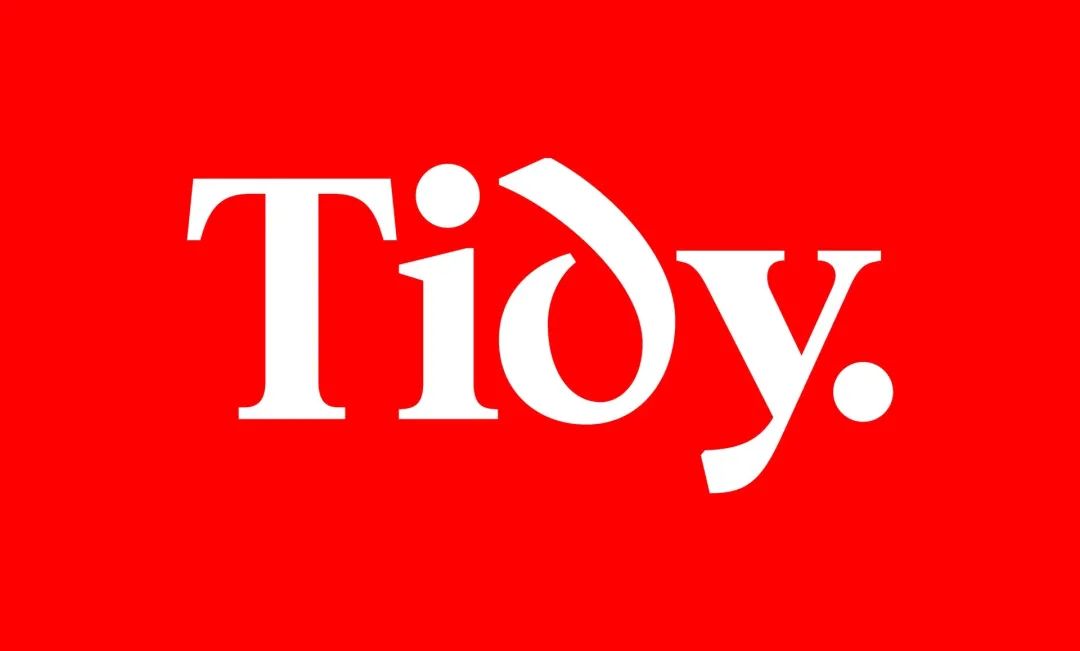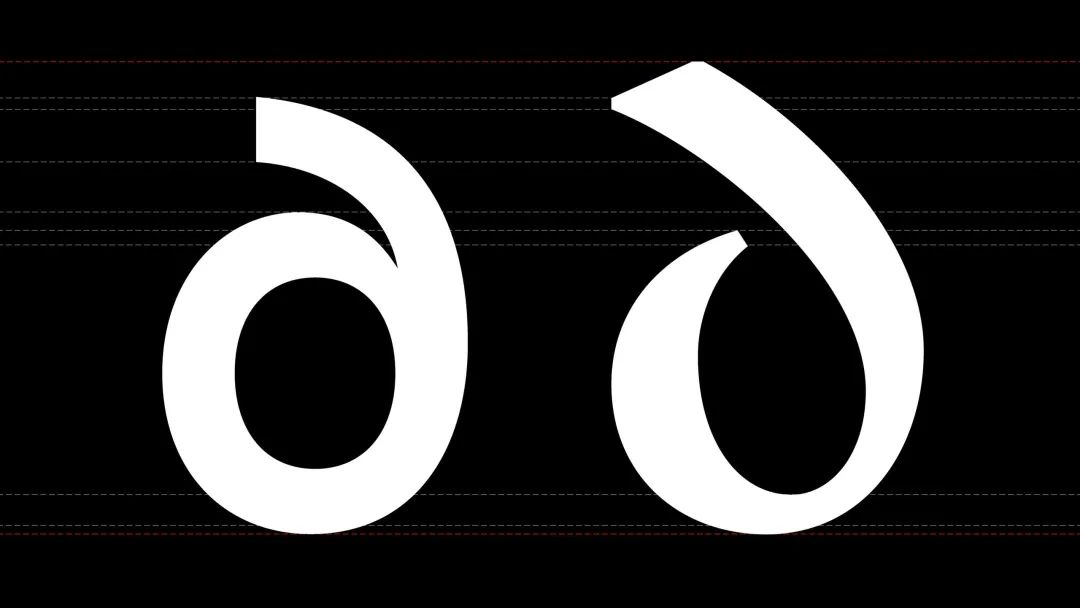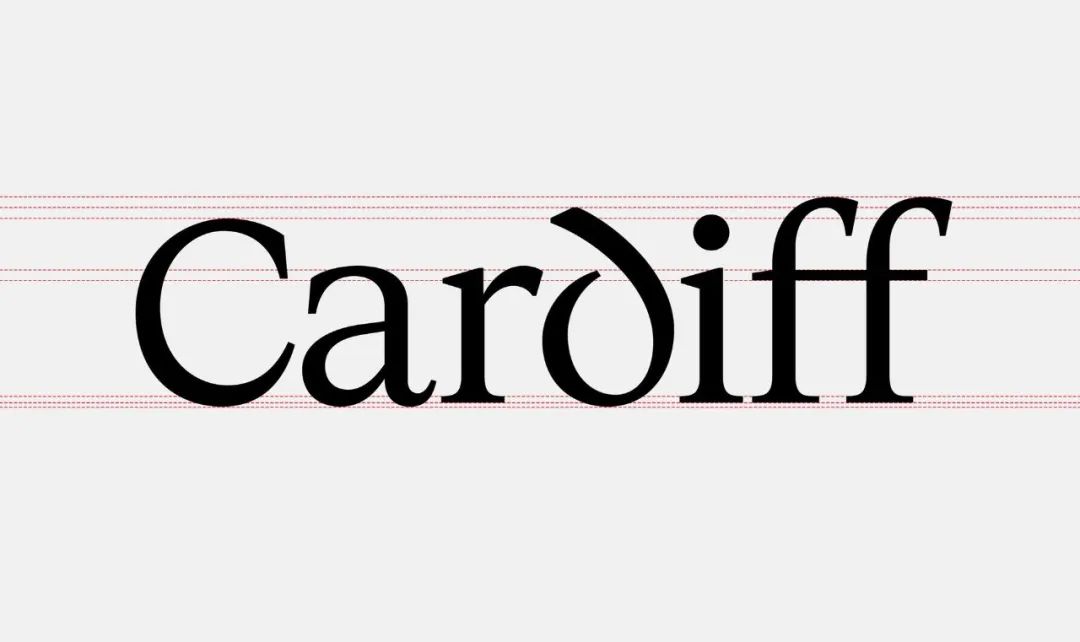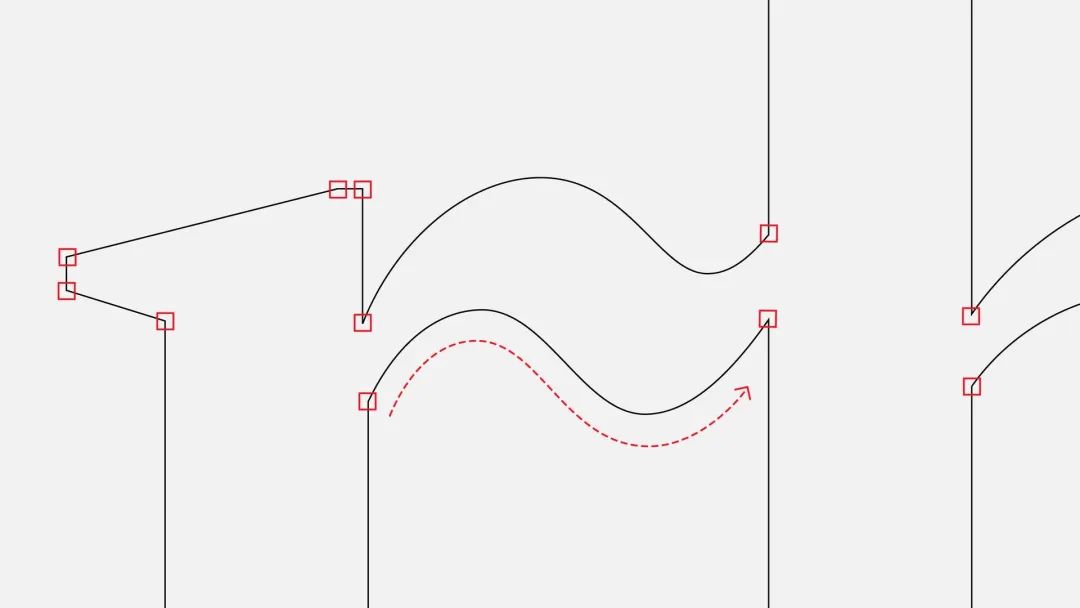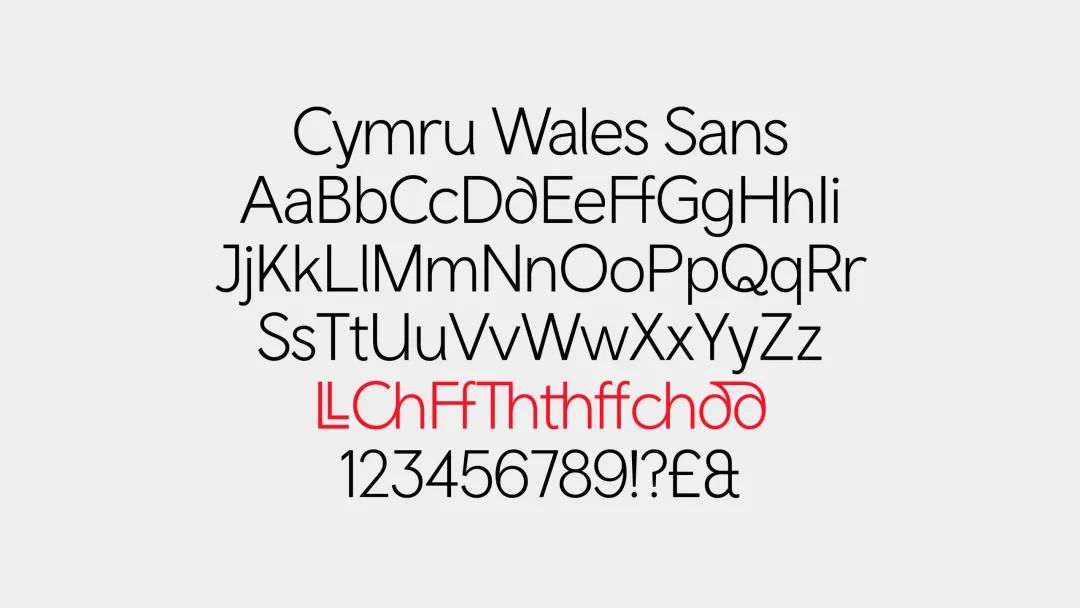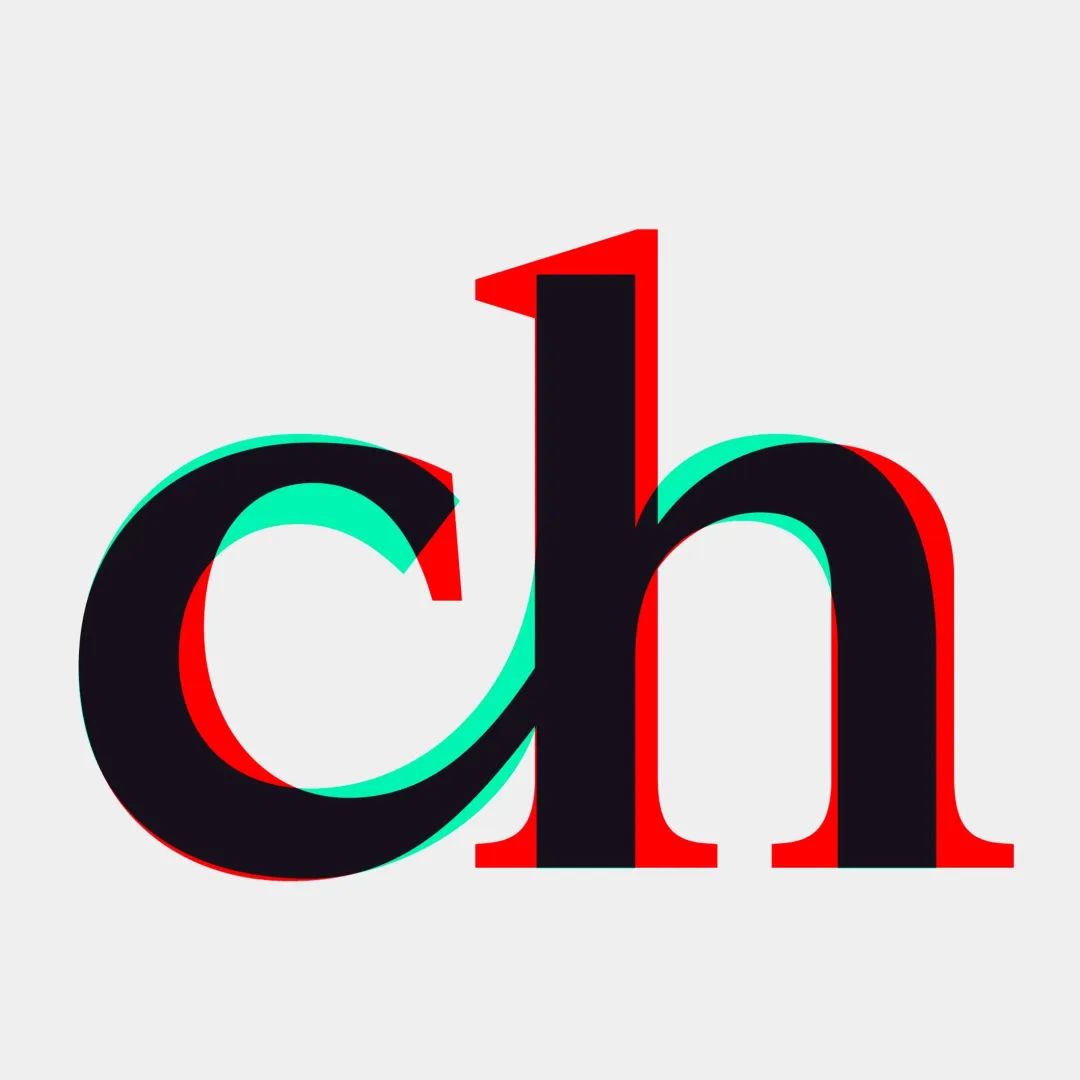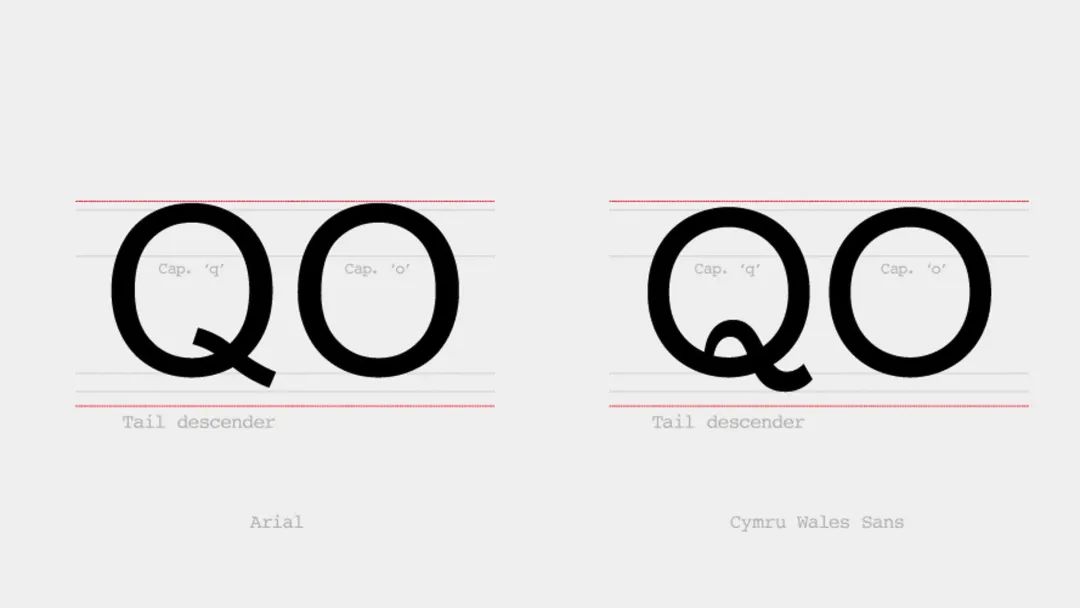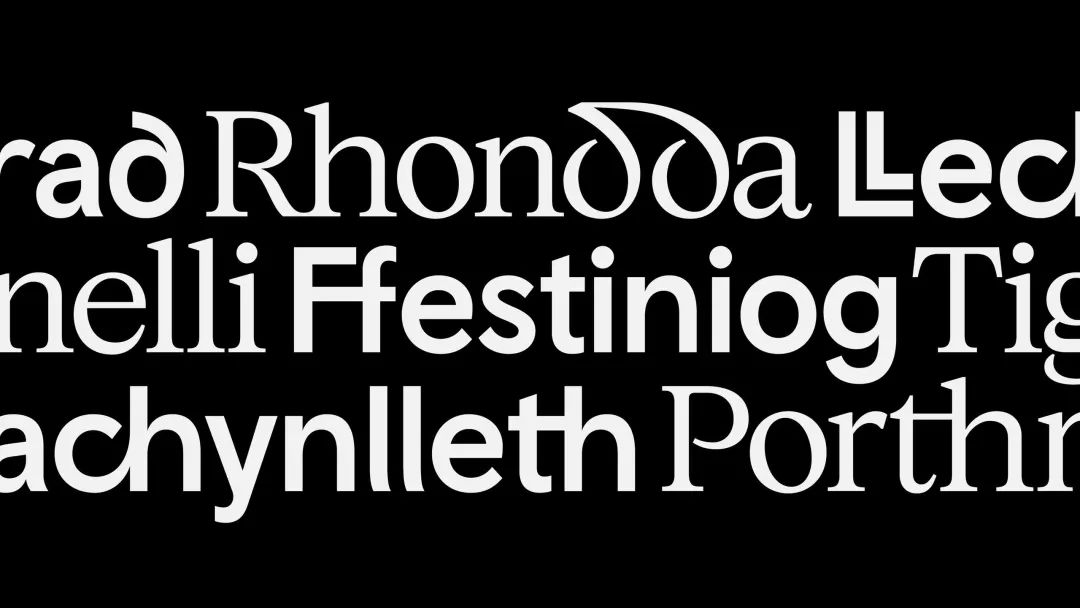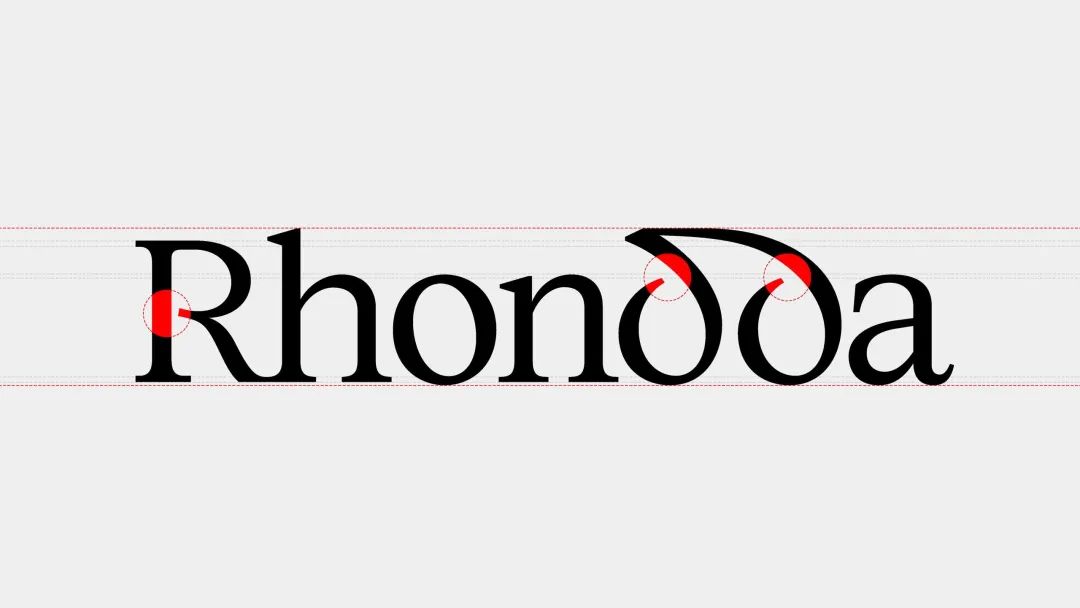
SMörgèsbord为威尔士语定制了一套字体
创建了一个独特的字体家族来代表威尔士向世界展示...
一个现代的字体家族,旨在以真实而富有创意的方式向世界展示威尔士,并将威尔士语言的起源和独特的语言特征放在首位。尽管定制字体是从威尔士印刷文化遗产中汲取灵感的,但要特别注意不要走入仿冒或模仿的领域。所有这三个委员会都是与Colophon铸造厂密切合作开发的,并由Joseph Burrin提供了额外的咨询服务。
该项目是受威尔士政府委托进行的,是该国视觉形象重塑的一部分。它采用了Smorgasbord最初于2017年设计的朴实无余的Cymru Wales Sans字体,同时还有一种衬线字体(用于长时间阅读)和一种用于当地交通系统的指定字体。
为了给版式注入一种独特的认同感和地域感,工作室追溯到了一些现存最古老的威尔士手稿,包括分别可以追溯到13世纪和14世纪的卡马滕黑皮书(Black Book Of Carmarten)和赫斯特红皮书(Red Book Of Hergest)。
在与 Colophon Type Foundry 的合作下,他们开始将这种语言的一些独特的风格特征融入到现代字体中。
最值得注意的是,它表达了威尔士字母与英语字母的区别。这些特征是两个字母的组合,如ph或ll,代表一个单一的声音。由于缺乏专门的数字字符,这些通常是用两个单独的字母拼写的,但它们实际上代表一个字母——很像德语的umlaut——并在填字游戏中占据一个单独的框。Smorgasbord的创意总监兼联合创始人迪伦·格里菲斯说:“威尔士字母表共有28个字母,有8个有向图。有足够的理由着手创建一个国家定义的定制字体家族。”除了有向图外,最显著的特征是d,它有一个向前弯曲的上升部分。格里菲斯说道:“弯曲的d在我们的两篇威尔士参考文献中都有广泛的使用,此外还有一些开放的弓形文字,其中字母B、g或R的圆形部分并不是完全闭合的。我们还觉得开放式的引入增加了一种当代风格的元素,将进一步增强字体的独特性,而不会陷入模仿或戏仿的境地。”
对威尔士文化遗产的认可可以在微妙的细节中找到,比如 Cymru Wales Serif 字体的倒角边缘,这让人想起该地区传统的石字雕刻工艺。
工作室还研究了冰岛语等其他少数民族语言的数字表达,以及阿拉伯语的草书字符,以寻找如何为字体设计注入鲜明个性的线索。
格里菲斯解释说:“冰岛人的性格为我们提供了一些线索,告诉我们如何最好地处理我们的曲线d。”
阿拉伯字体使我们创造了一种折叠式的带状手势,这种手势的特点是 Cymru Wales 衬线,即d、dd、ch、rh和l的叠加元素。工作室的另一个关键问题是保持语言的可访问性,尽管包括了鲜为人知的语言元素,如有向图。格里菲斯说:“我们可以预见,将可以被认为是‘外来’的字母形式引入字母表可能会给一些用户带来挑战,所以我们从一开始就与 Burdus Access 和应用寻路公司的团队合作,以确保这些有价值的易读性工具被认为是有价值的易读性工具,而不是语言障碍。”“所有的角色都有一个慷慨、开放的筹码。下降字母的长度比往常长,i和j上的圆点过大。我们还在 Cymru Wales Sans 中的垂直词干末端引入了笔画,以确保区分,例如,大写i和小写l‘s之间的区别。”威尔士官方交通字体看到 Cymru 威尔士 Sans 以所有大写字母呈现,带有印刷的实用字母,将被整个交通网络采用。目前,新字体系列仅限于政府宣传、市场营销和与推广威尔士相关的活动。但格里菲斯希望它的影响力能超越这一点。
他说:“展望未来,我们希望这些字体可以成为其他数字字体的催化剂,甚至可以看到人们将有向图融入到手写体中。”2019年的一项调查发现,尽管威尔士语是欧洲现存最古老的语言之一,曾有90%的人口使用威尔士语,但现在只有29%的威尔士人使用威尔士语。在英格兰的统治下,威尔士语被亨利八世于1567年废除。后来,在1847年的一次议会审查后,威尔士语被禁止在学校里教授,甚至被禁止在学校里说,因为英国人认为这是为了延续威尔士人所认为的“不朽”。然而,这门语言在1999年被恢复为学校的必修课后,近年来经历了复兴,并从指定的威尔士语电台和报纸转移到主流电视节目,如被 Netflix 选中的 Hinterland。格里菲斯解释说:“Cymru Wales 字体系列的创建符合威尔士政府到2050年拥有100万威尔士语使用者的愿景。”引用爱尔兰教师兼诗人帕德雷格·皮尔斯(Pádraig Pearse)的话说:“一个没有语言的国家就是一个没有灵魂的国家。”语言和排版对民族认同感的重要性也体现在最近的一系列其他项目中,如 Oli Grotesk 字体,它能够表达九种传统的印度文字,以及 Signato,它是为庆祝立陶宛独立100周年而创建的。